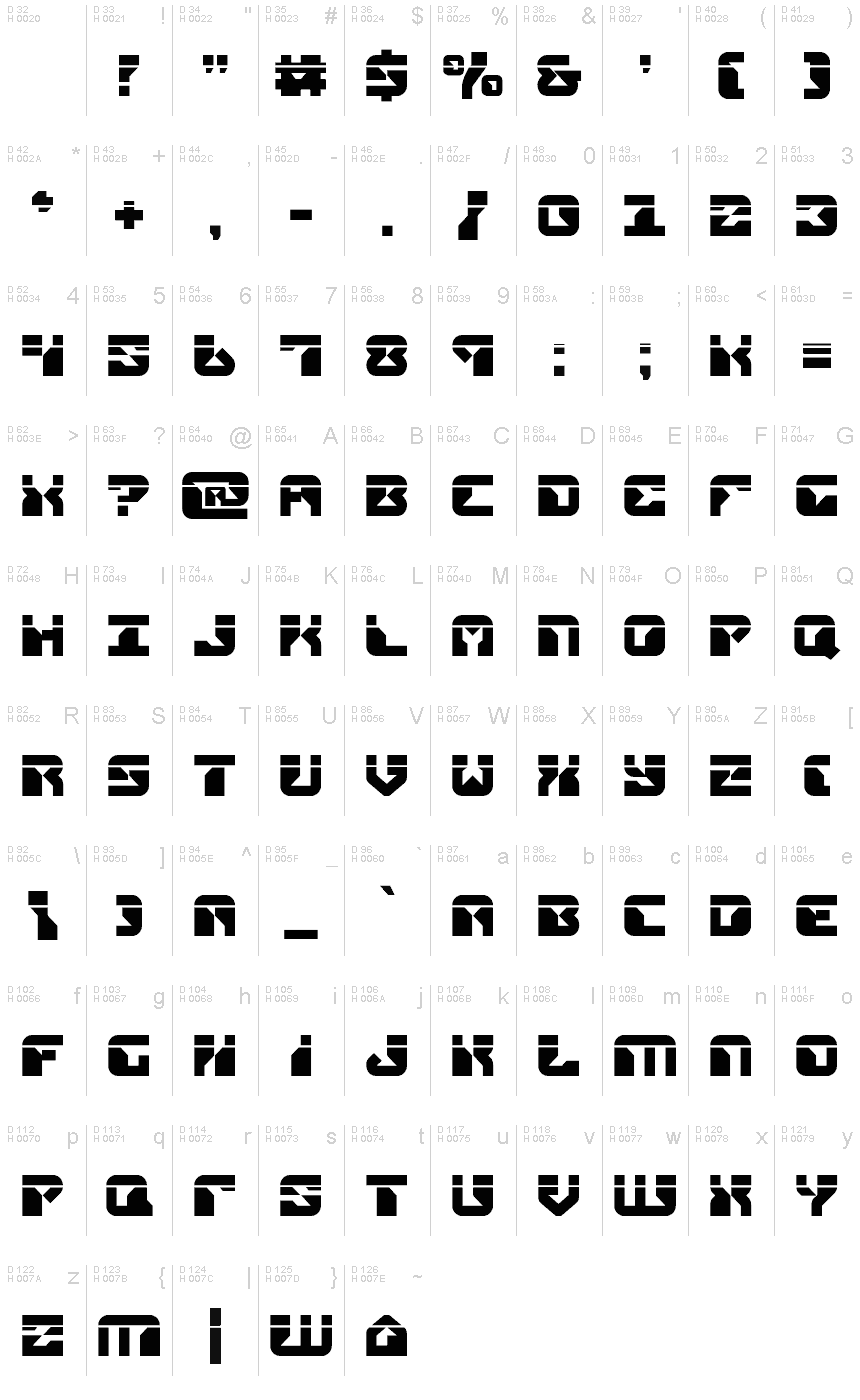
Replicant Laser od Iconian Fonts to darmowy, futurystyczny font display, bazujący na wielkich literach i wyróżniający się klimatem hard sci-fi. Litery sprawiają wrażenie wykrojonych jednocześnie ze światła i metalu, z szerokimi geometrycznymi formami, ściętymi narożnikami i ostrymi wewnętrznymi wycięciami, które nadają alfabetowi wygładzony, inżynieryjny rytm prosto z cybernetycznej estetyki ekranów z 2016 roku.
Font naturalnie pasuje do logo gier, plakatów w stylu synthwave, tytułów filmowych, identyfikacji wizualnej wydarzeń technologicznych oraz krótkich haseł, gdzie darmowy krój musi wyglądać na stworzony maszynowo, a nie neutralnie. Użyj go, gdy chcesz, aby wielkie litery samodzielnie budowały nastrój – szczególnie w przypadku krótkich nazw, monogramów i nagłówków, które zyskują dzięki jego segmentowej, laserowo wycinanej sylwetce.